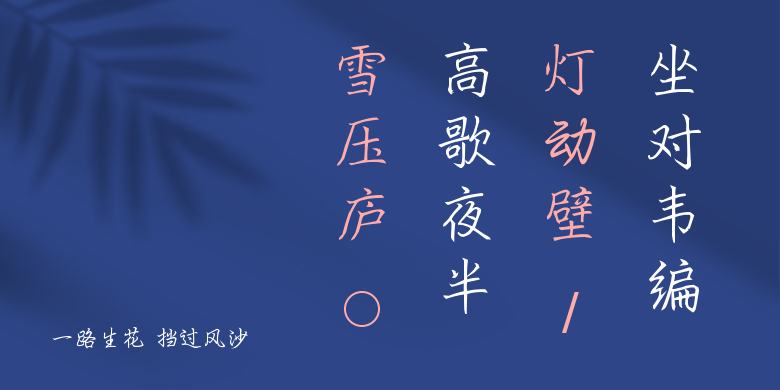
一路生花 挡过风沙
一路生花 挡过风沙,这款字体结构工整、笔画清晰,兼顾美观与易读性,适用于标题、正文、海报、包装、LOGO 等多种场景。字形优雅稳定,风格百搭耐看,适配日常排版与创意设计,让文字呈现更舒适、更具质感。一路生花 挡过风沙一笔一画,皆是细节,以均衡的比例、流畅的线条打造舒适视觉体验,字形端正大气,风格简约现代。无论是商业设计、品牌宣传还是日常排版,都能轻松驾驭,让文字更有格调与力量。一路生花 挡过风沙字体下载。